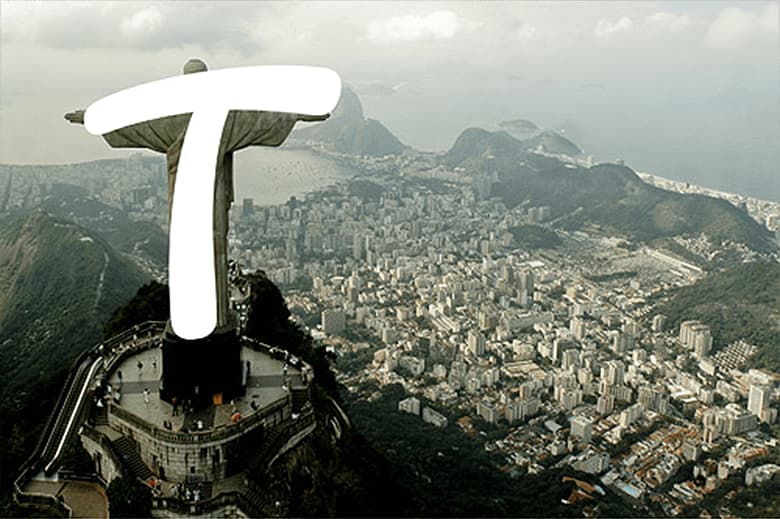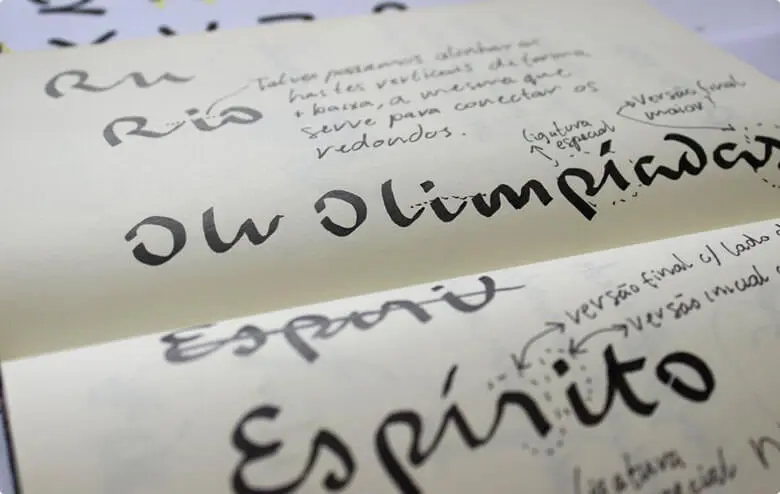
躍動感あふれる「Rio 2016 font」の着想の源泉
2012年のロンドンオリンピックのフォントに続き、2016年のリオデジャネイロオリンピックのフォントを担当したのは、タイプフェイスデザインを行う会社Dalton Maag。
直線的でシャープなロンドンオリンピックのフォントとは対照的に、柔らかく丸みを帯びたリオデジャネイロオリンピックのフォントは、一風変わったものから着想を得ていました。
テーマは「情熱と変容」
Rio 2016 font
は、リオデジャネイロオリンピックとパラリンピックのエンブレムのテーマである「情熱と変容」を描いたデザインです。
引用元:リオデジャネイロオリンピック 公式サイトオリンピック・パラリンピックの精神はアスリートの敏速な動きを意識した流動的なラインに、伝染性のエネルギーは文字の異なる高さや文字同士の太い接続部分に、活気ある性質は文字の全体的なデザインの中に反映され、文字ごとに異なるさまざまな曲線や高さは、ブラジルの人々の持つ温かさや楽しさを表現しています。
引用元:リオデジャネイロオリンピック 公式サイト太いストロークと細いストロークの強いコントラストは、紙に筆をいれ何度も手描きして調整を重ねたデザインの過程を見ているようです。
引用元:THE FontFeed小文字の“m”はコパカバーナの歩道、“T”はリオデジャネイロを見下ろす救世主キリスト像からといった、街や自然の景色から着想を得てつくられた文字もあります。
制作の裏側
引用元:リオデジャネイロオリンピック 公式サイト何度も微調整を繰り返し完成したRio 2016 font。
引用元:リオデジャネイロオリンピック 公式サイト手描きフォントのRio 2016 fontはすべての軸が曲線でできているため、次に続く文字にどう繋げるかがとてもむずかしく、そこが一番苦労した点なのだと、Dalton Maagのブラジル人デザイナーFabio Haagさんは語っています。
引用元:THE FontFeed次に続く文字によって形を変え、スクリプト体のリズムを活かしてバランスをとるという設計は、OpenTypeの機能を用いることにより実現しました。
「多様性の調和」
文字により高さや太さが異なり、独特の曲線をまとったこのフォントは、まさにオリンピックにふさわしい「多様性の調和」をあらわしています。
引用元:THE FontFeed2016年8月に開催されるリオデジャネイロオリンピック。どんな動きからどの文字が生まれたか、アスリートたちの動きとRio 2016 fontを重ねあわせて見てみると、また別の楽しみ方が出来そうですね。